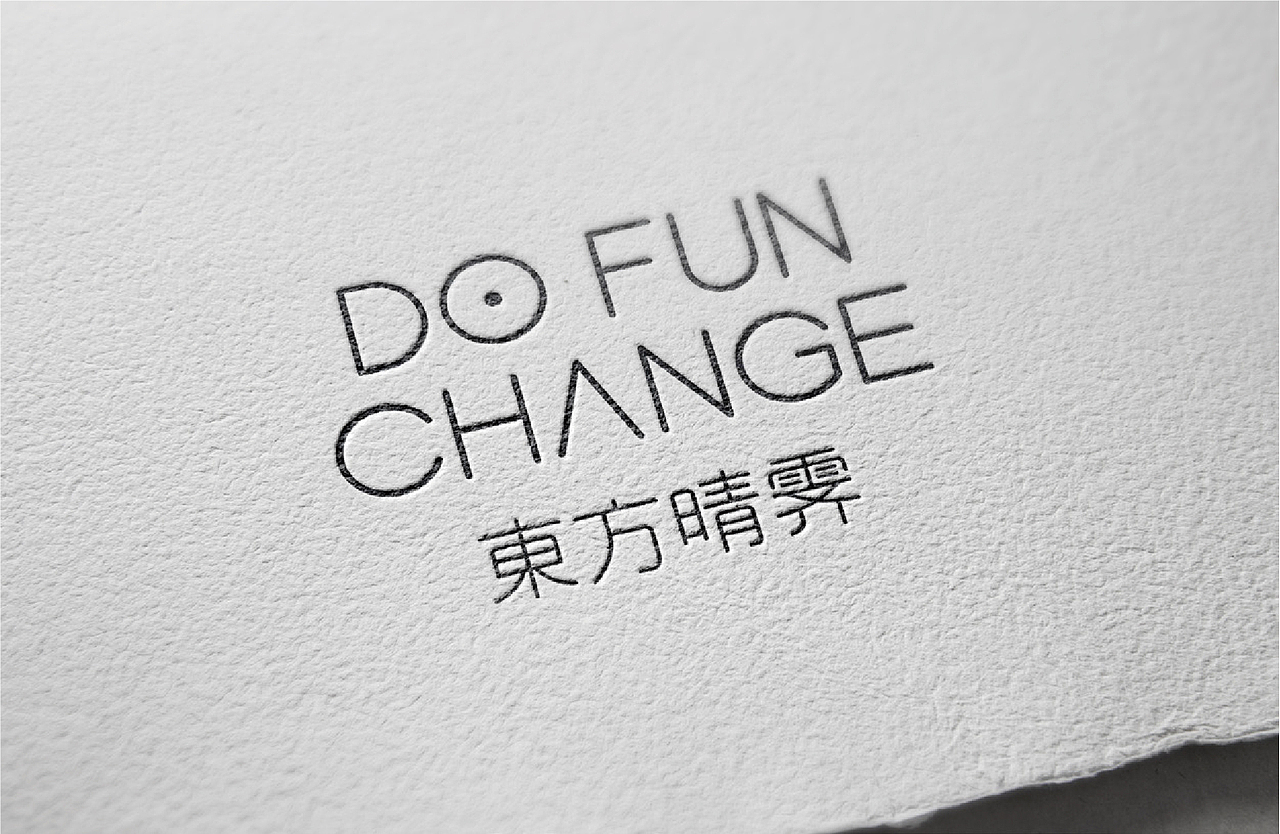
【品牌设计】东方晴霁·植物芳疗护肤
以品牌主导设计 以设计带动品牌
东方晴霁 委托BM策略,进行品牌全案设计与产品体系设计
从0到1打造全新品牌力
品牌战略重塑,视觉升级2.0
【标志设计】
升级之前的标志以中文字体标为主,后期增加英文辅助。委托方认为早年的设计已经不符合现在的审美,需要进行品牌视觉升级,希望在注入新鲜元素的同时增加品牌力。
升级之后的标志是英文字体标。以“日出东方”作为创意点,进行发散延展,结合甲骨文的太阳图腾,让设计不仅实现了客户提出的极简国际大牌的视觉要求,而且也实现了中西结合的视觉碰撞。用标志阐述“东方晴霁”作为国货品牌的使命与追求。